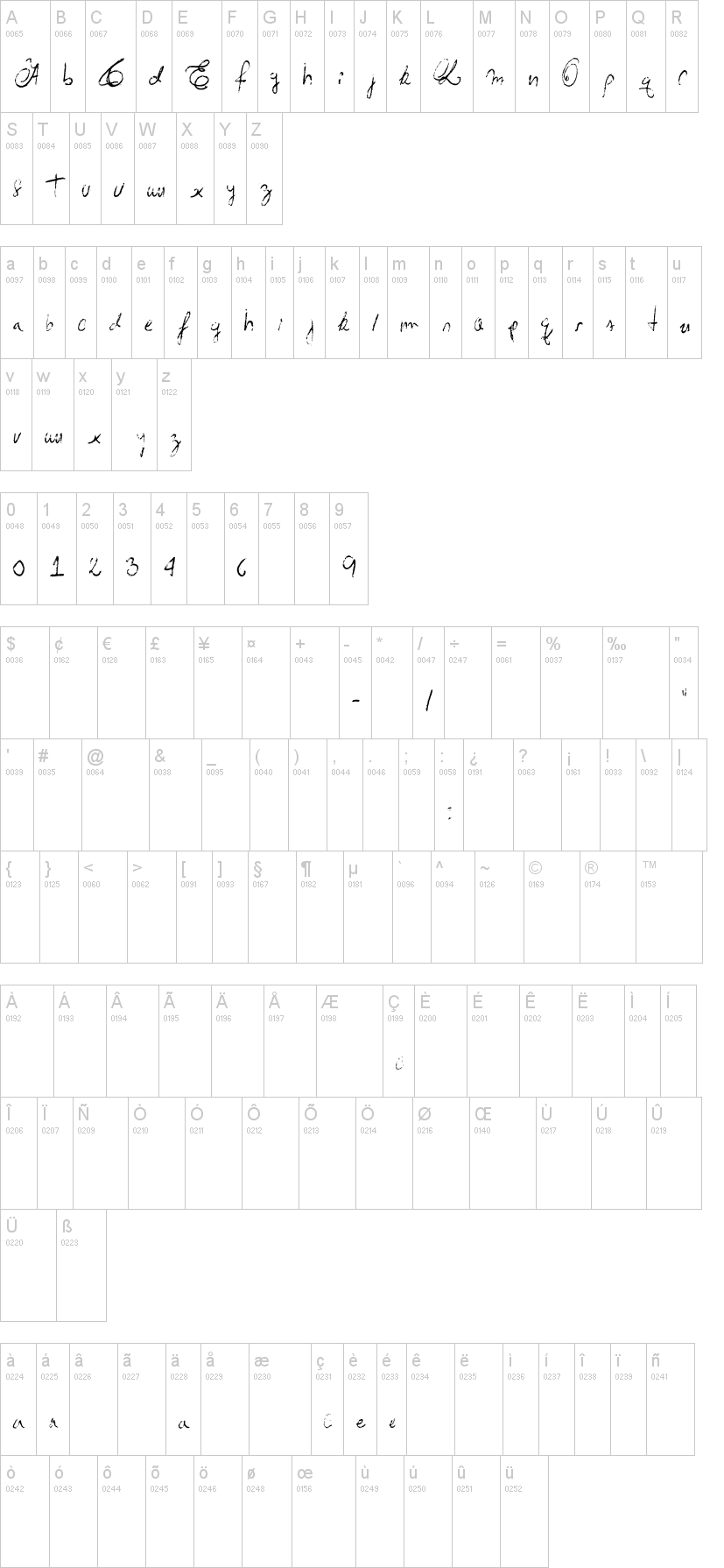
Acid Rain 字体是一种免费的手写风格字体,由设计师 Billy Snyder 创作。该字体的特点是字母错综复杂,带有草图和涂鸦的感觉,有点像是在墙上喷涂的字体。它包括大小写字母、数字、标点符号和一些特殊字符,适用于各种设计项目,如海报、标志、标题和书籍封面等。此外,该字体也可以用于个人和商业用途,无需付费或授权,使其成为许多人喜欢的字体之一。内容介绍
Acid Rain是一款非常不错的手写艺术字体,具有很好的视觉感,适合于文化类的宣传设计、商业类品牌的广告和产品包装设计以及个性化文字排版等较多场景。